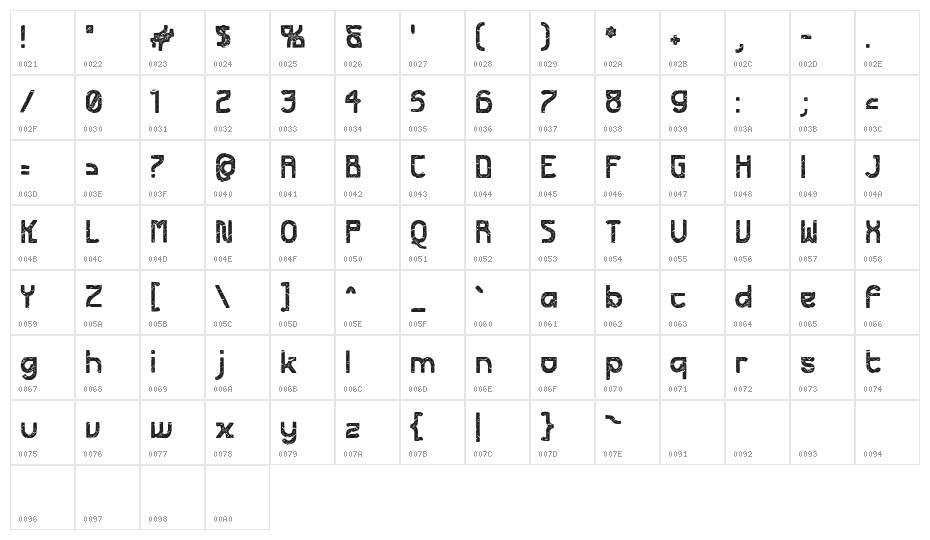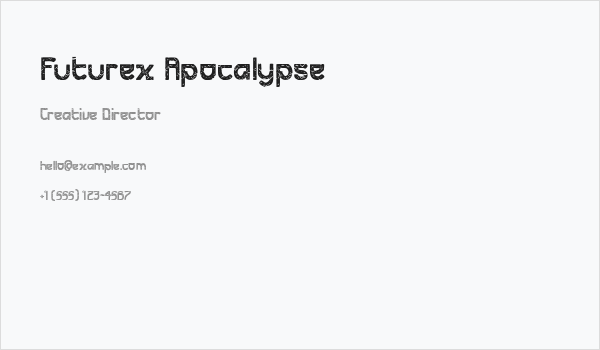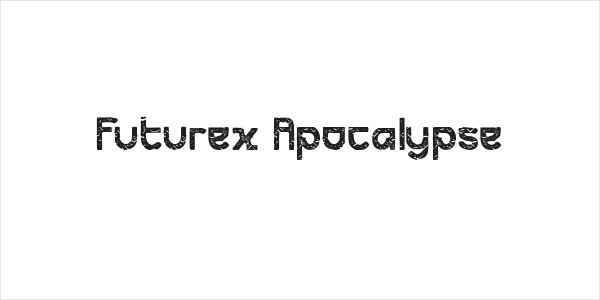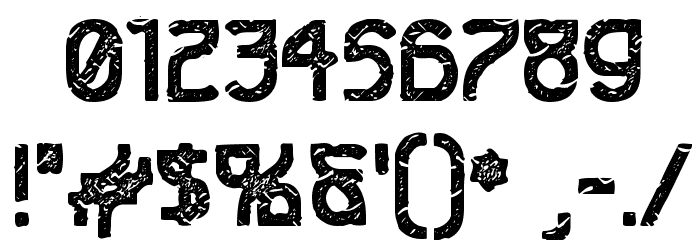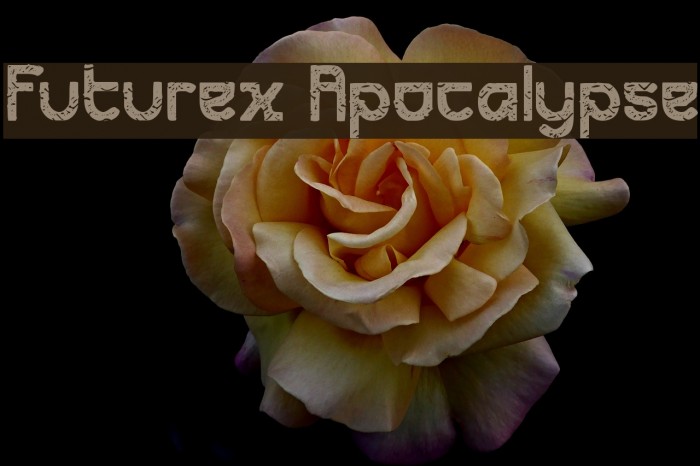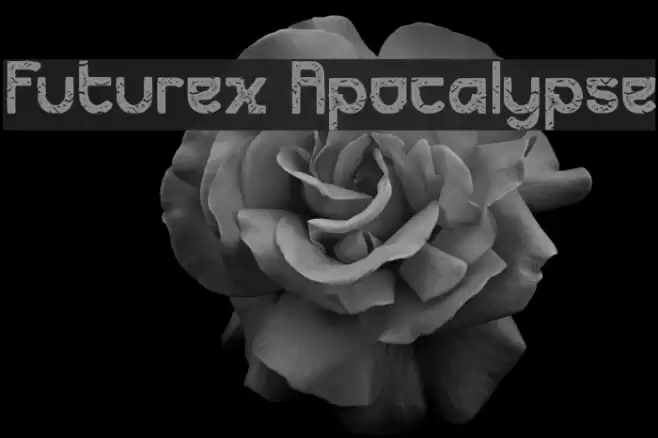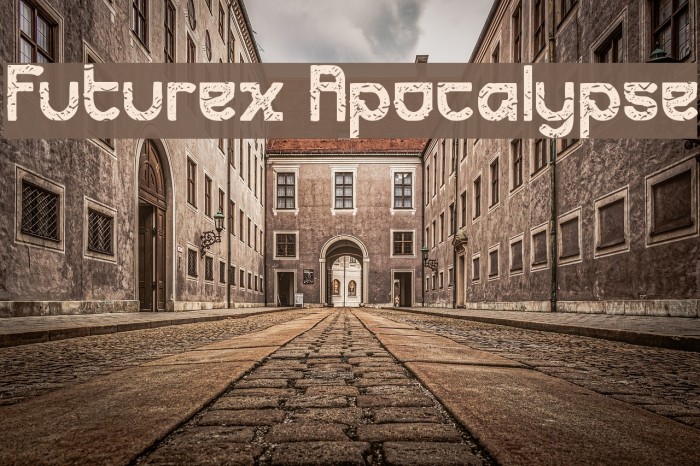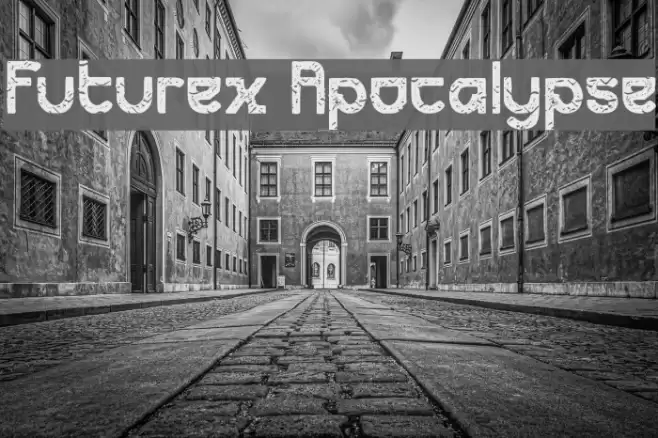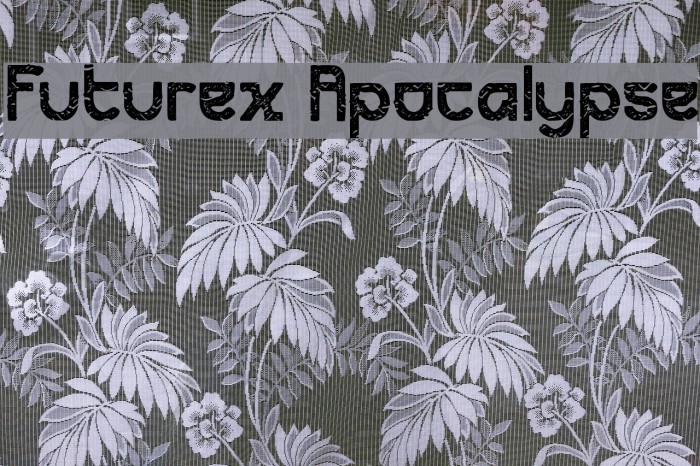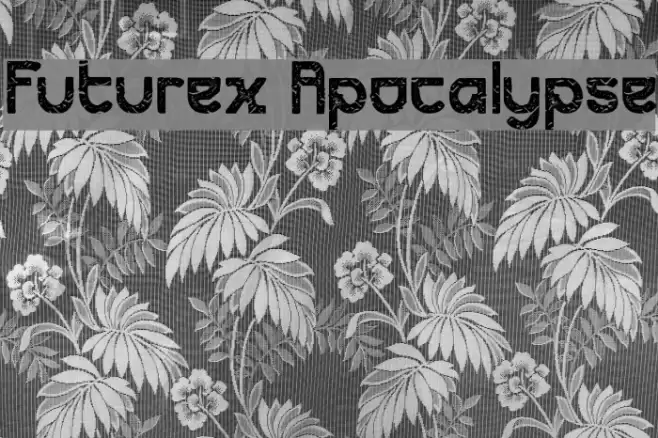
Futurex Apocalypse Font
Fonts by Apostrophic Lab
| Proyectos propuestos | Perfect for album covers, movie posters, video game titles, and branding for edgy or alternative products. |